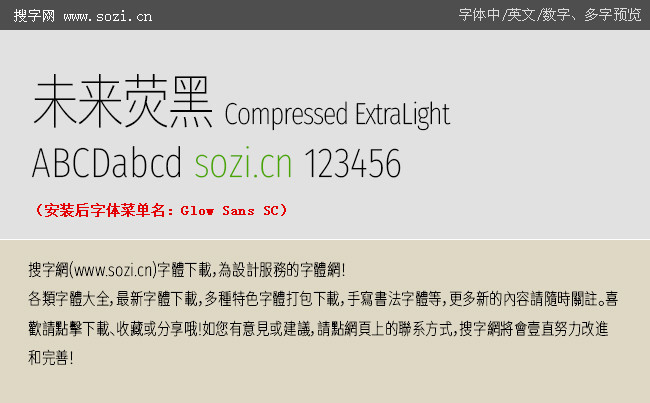
未来荧黑-Compressed-ExtraLight
搜字网给大家提供一款未来荧黑-Compressed-ExtraLight中文字体下载,未来荧黑-Compressed版是未来荧黑中的一个瘦长体系列,未来荧黑是一个基于思源黑体、Fira Sans和Raleway的开源字体项目,该字体由八种字重,字体中宫与字面更加收敛,细节上面处理更加的干练,适合应用于艺术设计、平面宣传设计、网页设计等广告设计。